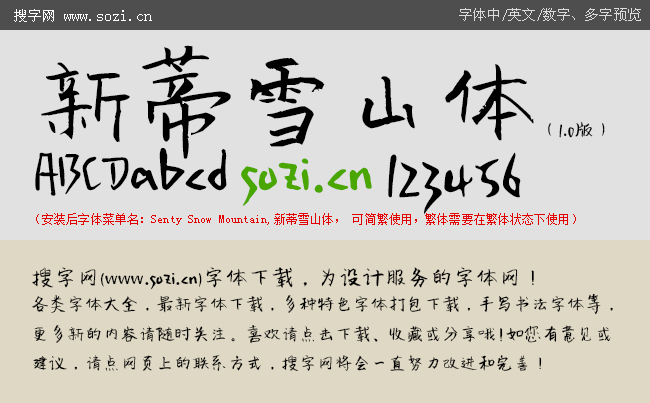
新蒂雪山體
搜字網(wǎng)提供一款新蒂雪山體中文書法字體下載,新蒂雪山體是一款非常漂亮的手寫風(fēng)格書法字體,字體飄逸大方,結(jié)構(gòu)合理沉穩(wěn),整體字形非常大氣,適合應(yīng)用于廣告設(shè)計、名片設(shè)計、包裝印刷、海報設(shè)計等應(yīng)用。